今回は、「サンリオ」の世界観にぴったりな日本語フリーフォントをご紹介します。
サンリオといえば、ハローキティやマイメロディ、シナモロールなど、キュートで夢いっぱいのキャラクターたちが思い浮かびますよね。そんなファンシーでほんのりレトロ、甘くてときめく世界観を表現するには、フォントにも“かわいさ”が欠かせません。
今回は、まるっこくて愛らしいものから、ほんの少し毒っ気のある“ゆめかわ”テイストまで、サンリオ的なかわいさにフィットする日本語フリーフォントをピックアップしました。キャラクター紹介やグッズ風デザイン、POPなどにもオリジナルグッズを制作する際などにおすすめです。
「サンリオ」におすすめのフォントまとめ
以下のサンプル画像は本記事で紹介している一部ですが、サンリオの世界観にぴったりな可愛らしいフォントデザインをまとめてみました。
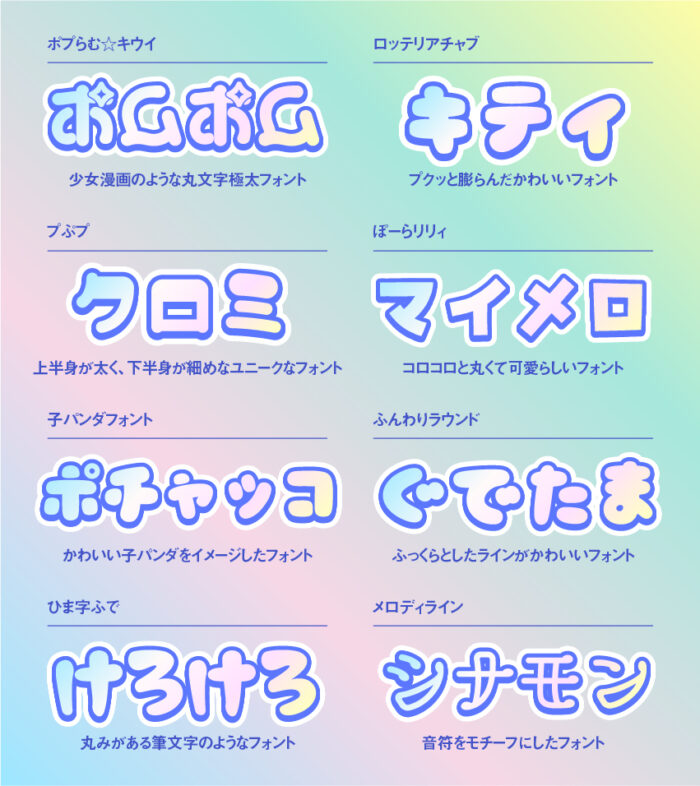
ポプらむ☆キウイ
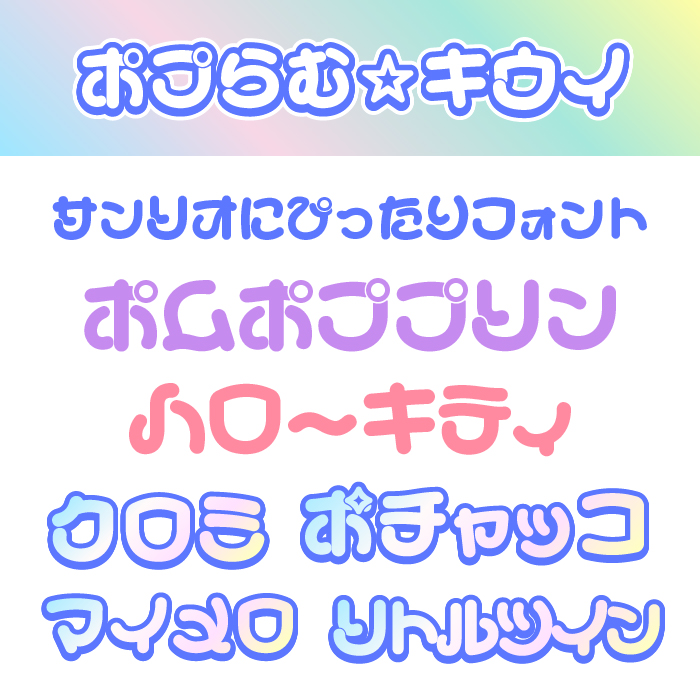
ポぷらむ☆キウィフォントは、星やハートのようなモチーフがちりばめられ、甘さの中にちょっとした遊び心が光るフォントです。サンリオの世界観にぴったりです。
ロッテリアチャブ
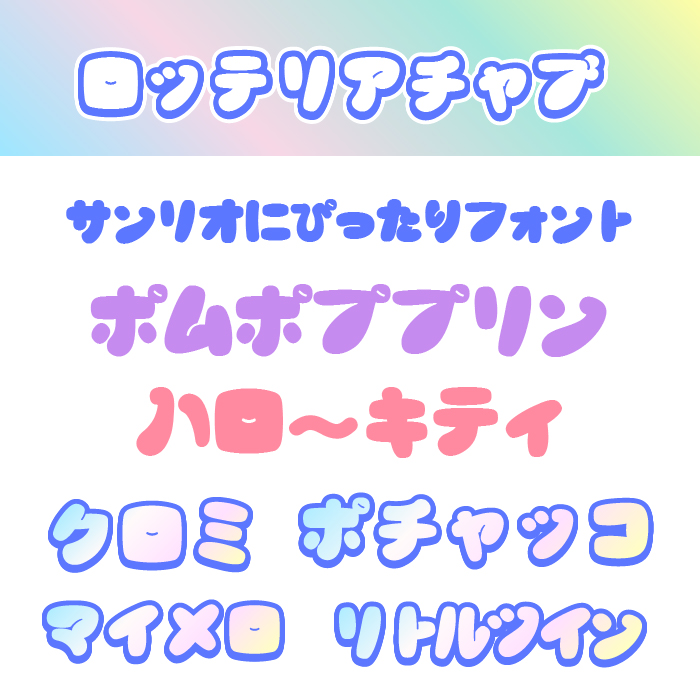
ロッテリアチャブフォントは、韓国ロッテリアが公式で提供しているフォントです。手描き風の味わいとレトロポップなシルエットが合わさった、元気でユニークで可愛らしい雰囲気のフォントです。
ぽーらリリィ
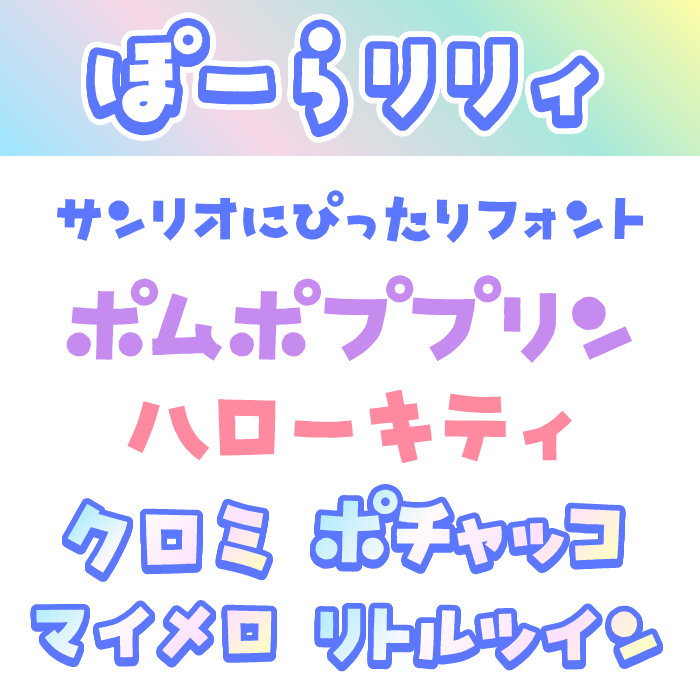
ぽーらリリィフォントは、ほんのりゆるんだ線とリズム感ある配置が、素朴でいて夢見がちな印象を与えるメルヘン調のフォントです。
ふんわりラウンド
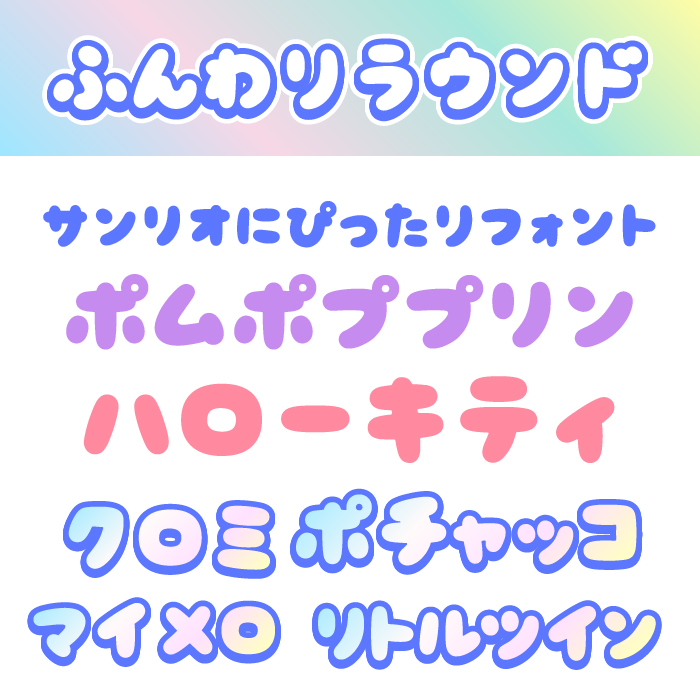
ふんわりラウンドフォントは、ふっくらした輪郭と優しい丸みが親しみやすく、どんなサンリオのキャラクターの世界観に溶け込む愛らしいフォントです。
まるチョコ
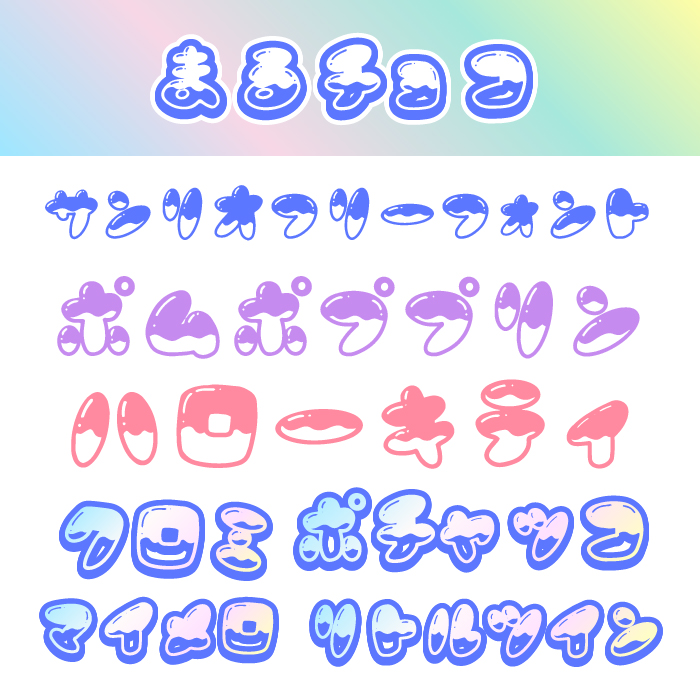
まるチョコフォントは、チョコレートのようなツヤと厚みが愛嬌たっぷりで、とろけるような甘さを感じるユニークなフォントです。お菓子っぽいキャラクターにぴったりハマります。
Cherry Bomb
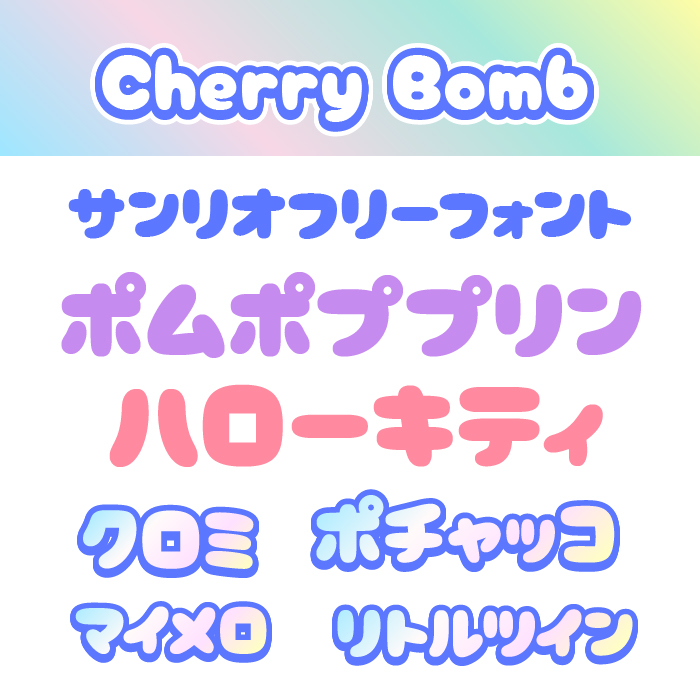
Cherry Bombフォントは、ポップさとやわらかさを兼ね備えた形状で、明るく楽しい気持ちをそのまま文字にしたようなフォントです。
子パンダフォント
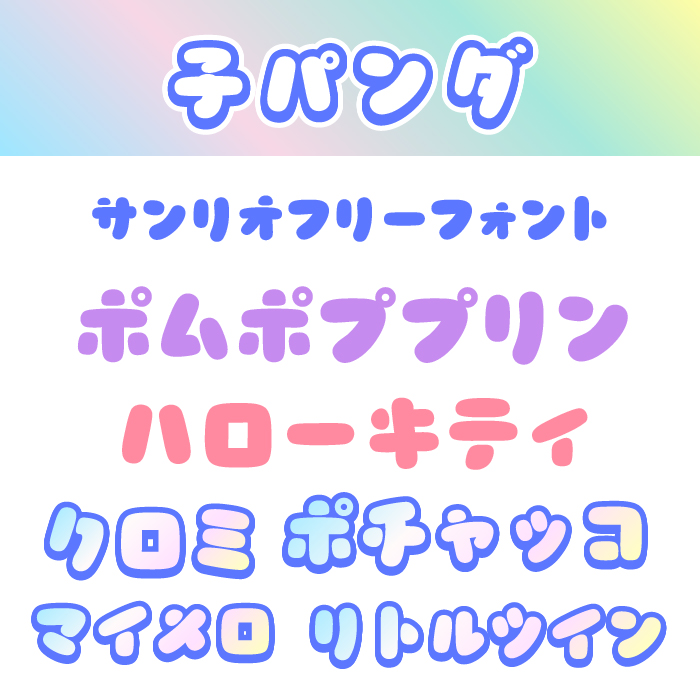
子パンダフォントは、ふにっとした柔らかな輪郭が特徴で、幼くて可愛らしいキャラクターの無邪気さを引き立てる素朴で優しいフォントです。
メロディラインフォント
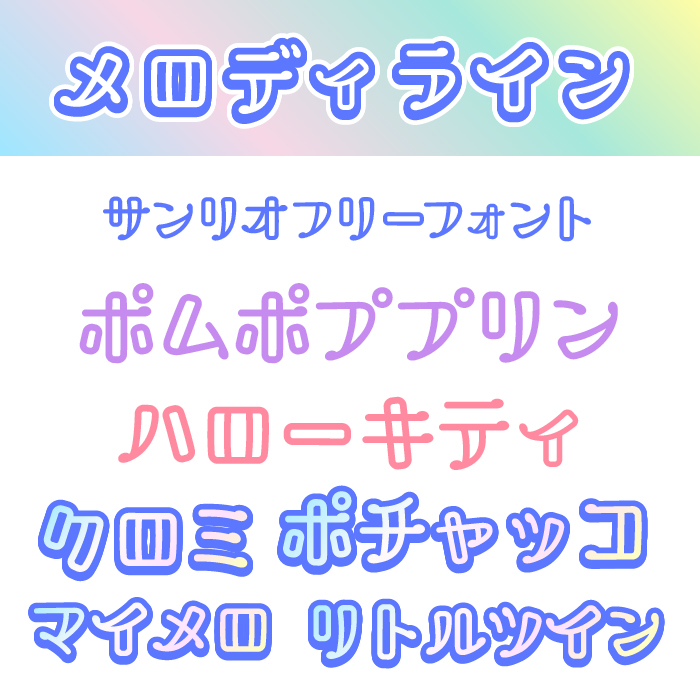
メロディラインフォントは、音楽のように軽やかでリズミカルな印象を持ち、丸みのあるアウトラインが特徴のポップでかわいいフォントです。パステル系のデザインや夢かわ系のロゴにぴったりです。
プぷプ
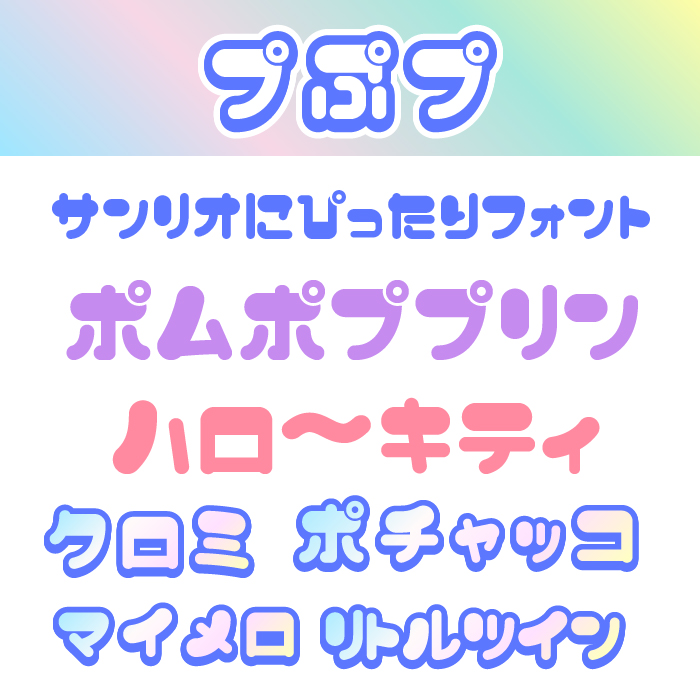
ぷプぷフォントは、角丸のつぶつぶ感と膨らみが愛くるしく、まるで飴玉のようにカラフルでキュートな雰囲気を持ったフォントです。